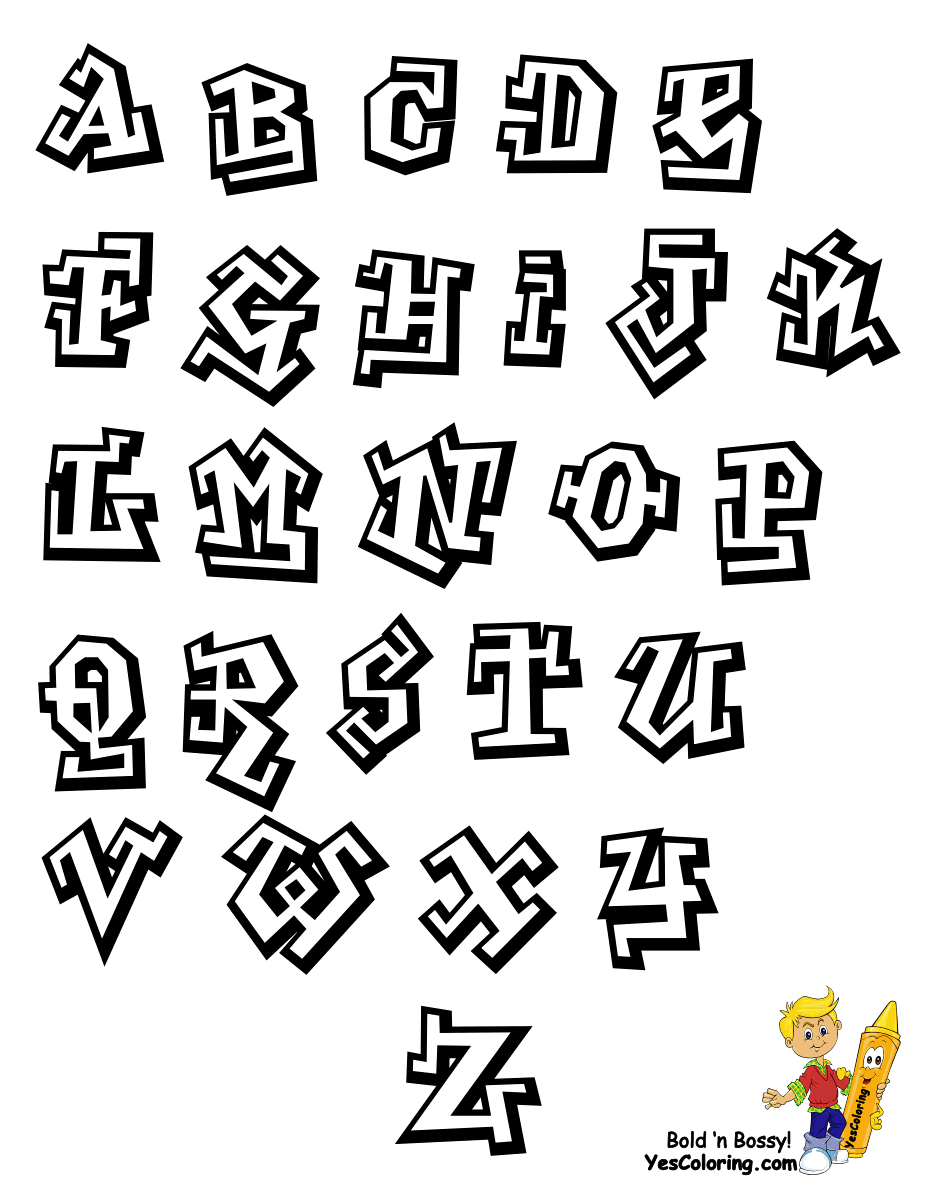
Алфавит тегов. Семь кириллических шрифтов граффити
About Graffiti Fonts
Graffiti is usually appeared as graphics or lettering scratched, scrawled, painted or marked in any manner on property. Graffiti has existed since very ancient times in Ancient Greece and the Roman Empire. In ancient Rome, people don’t have a photocopier or a fax machine or newspaper, and when you have a written message to let other people know, you scratched it on a wall. In modern times, however, graffiti is considered illegal in a lot of countries. But a country that with significant tradition in graffiti is Brazil and Sao Paulo, one of the largest cities in Brazil, is considered to be the current center of inspiration for graffiti artists.
Graffiti can have different styles. Tagging is the simplest type of graffiti, usually done quickly in spray paint, markers or pens and lacking artistic form; A throw-up involves more work than tagging, usually having two or three colors and done in bubble letters; Stenciling can be a quick way to produce more complicated graffiti designs and by using two or more layers, you can produce color-rich designs; Wildstyle is a form of graffiti that was made popular by graffiti artists like Tracy 168, Zephyr in NYC.
Graffiti in Wildstyle is relatively more complicated and artistic. There are other forms of styles such as blockbuster, hip-hop, heaven, stickers, wheat pasting, etc. So there are a lot of styles of graffiti, hence, graffiti fonts.
Depending on your preferences, there are many fonts that can be used for graffiti purposes such as bubble fonts, stencil fonts , outline fonts etc. However, for complicated graffiti styles, they can never be achieved by fonts. Graffiti fonts can be a good way to study graffiti letters or graffiti alphabet, but you really should learn to express in your style. Get inspired and check out our collection of free graffiti fonts , or use our graffiti text generator below.
Произведение (сокращенно от «шедевр») — картина, написанная от руки. Они содержат не менее трех цветов, и их раскрашивание занимает больше времени. Произведение в очевидном месте вызовет уважение художников со стороны других художников, потому что стоять на очевидном месте и рисовать на стенах, где граффити является незаконным, — большой риск.